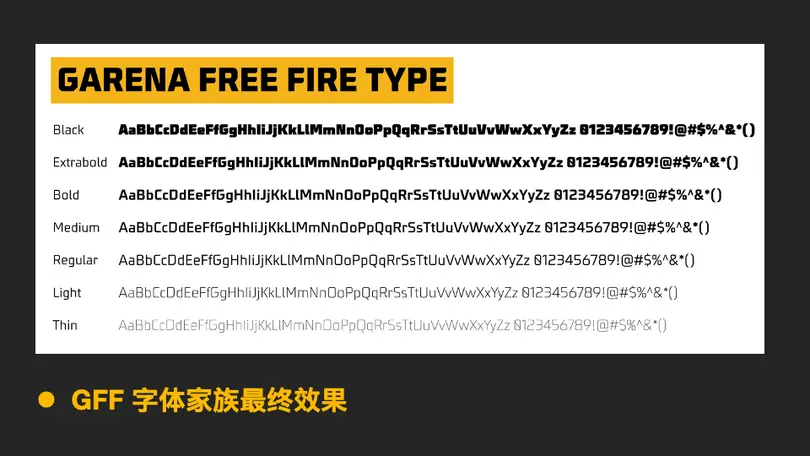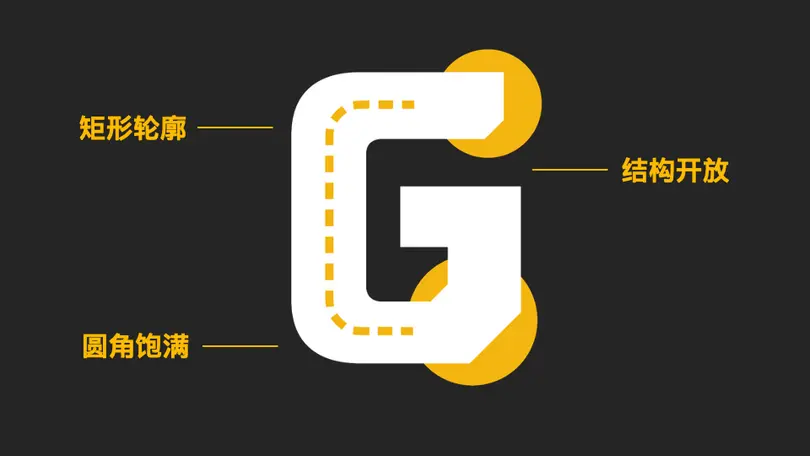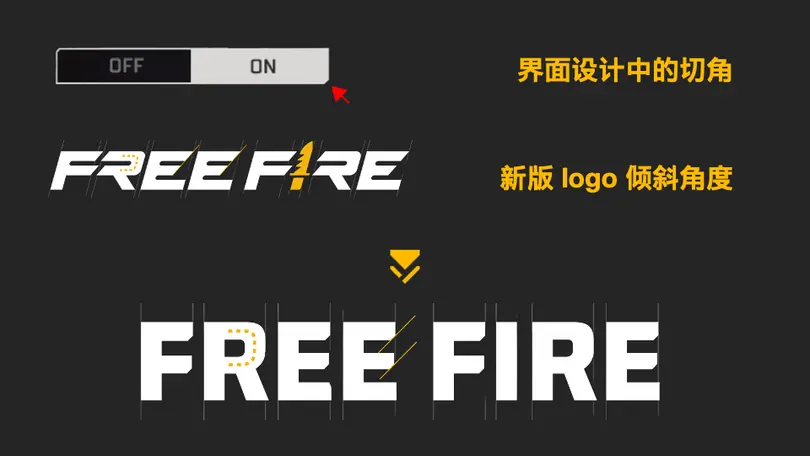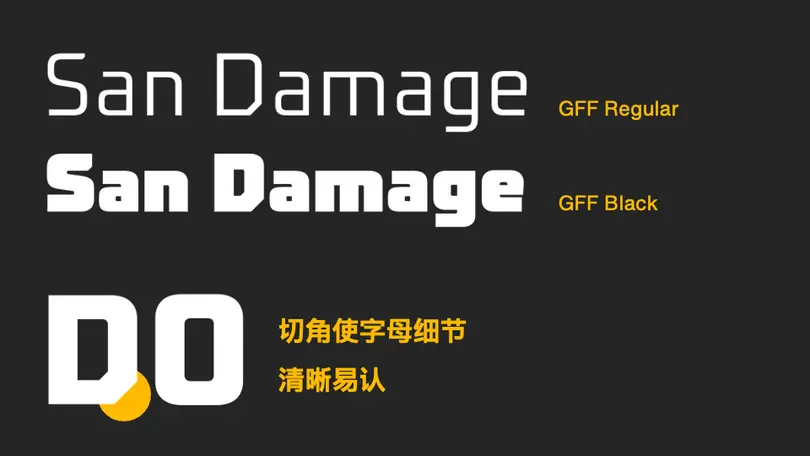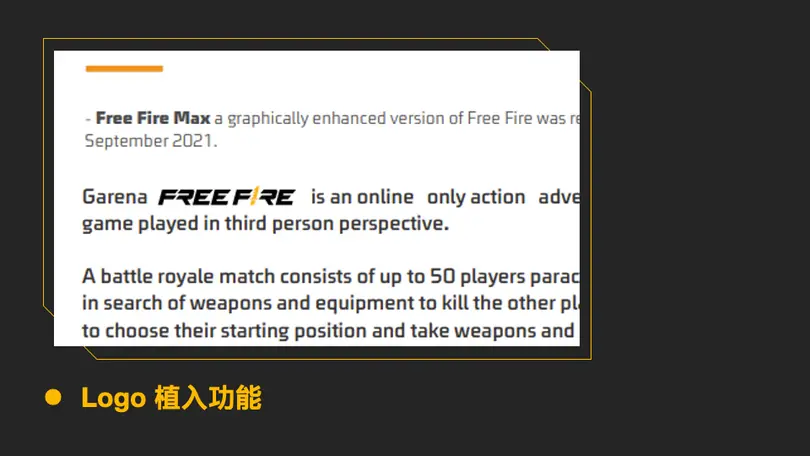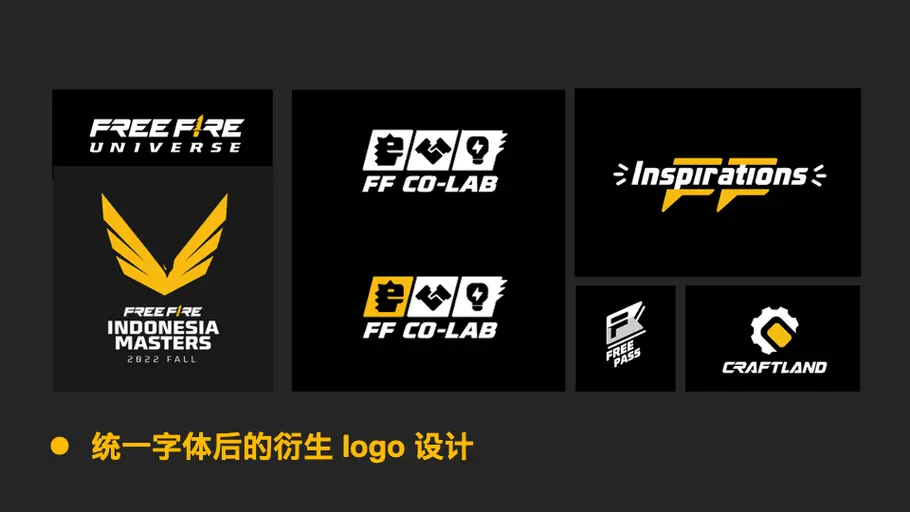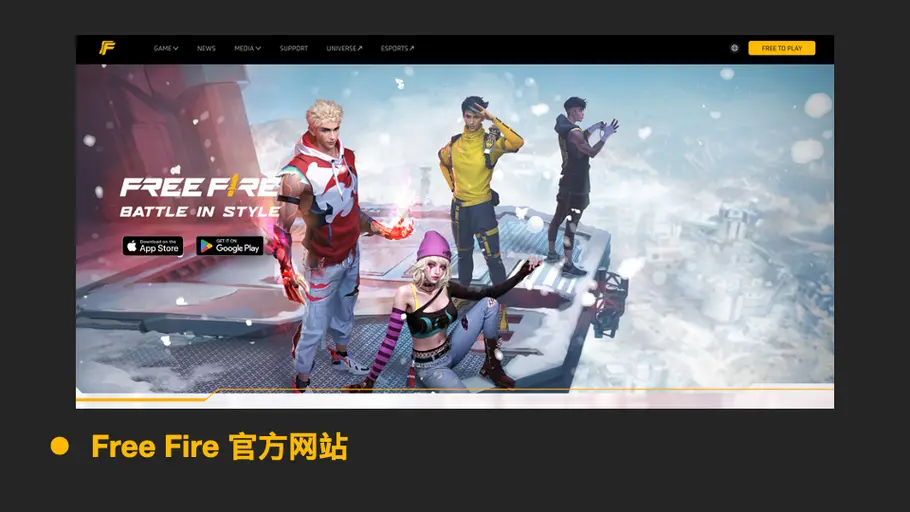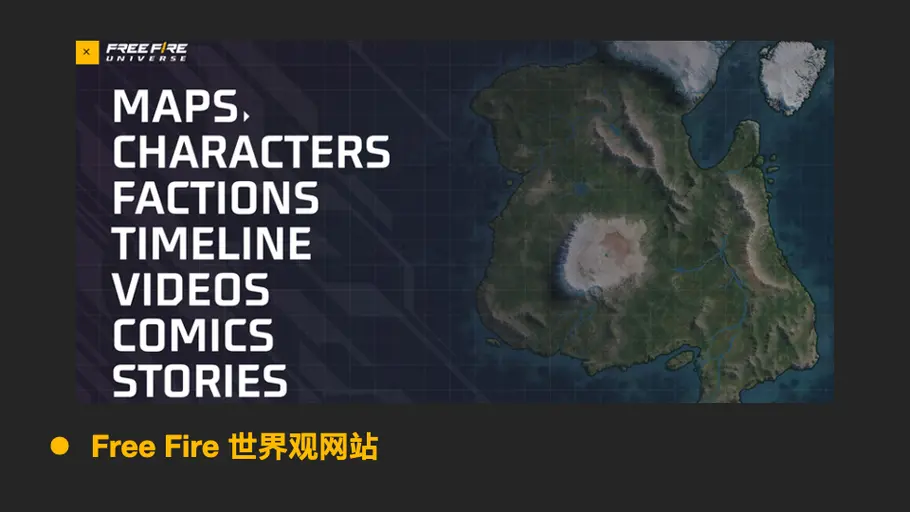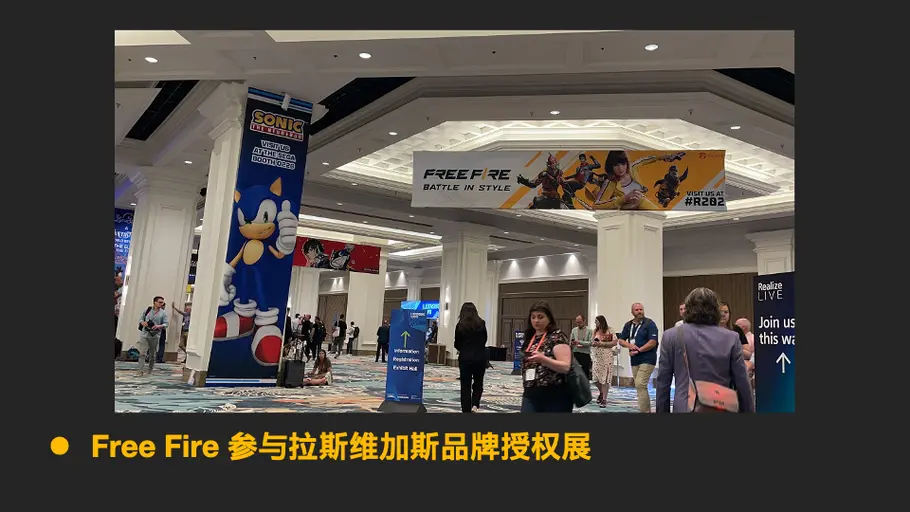
Garena 是知名的游戏开发及发行商,Free Fire 是其旗下自研的大逃杀类动作射击手游。自 2017 年发行至今,Free Fire 已向全球 160 多个国家和地区的玩家传递愉悦优质的游戏体验,在 2021 年达成了全球 10 亿次下载,曾连续三年问鼎全球下载量最高手游。
品牌升级挑战
伴随如此亮眼的成绩,Free Fire 在 2022 年迎来其发行五周年的里程碑,启动了游戏界面及品牌形象全方位的升级,并把“酷”与“轻”作为此次升级的视觉内核。
而字体的选用,逐渐浮现为升级过程中的关键环节。对于游戏界面,Free Fire 此前选用的授权字体虽然在风格上相对匹配,但字形窄粗,可读性欠佳,语种支持也有限;此外,自由度极高的本地化运营,也带来视觉形象不统一的潜在问题,其中字体的不统一成为主要原因。
字体设计细节
蒙纳字体创意总监小林章领衔指导的设计师团队与 Free Fire 团队紧密合作,对比多款现有字体,结合游戏应用实际需求,敲定了基础字形方案,并不断丰富更多细节,最终呈现 GARENA FREE FIRE TYPE 字体家族,简称 GFF Type。
风格与易读的极致平衡
GFF 基于矩形轮廓,结构开放,圆角饱满,笔画粗细均匀,构成了潮酷有力的基础风格。
同时,蒙纳设计师注意到了 Free Fire 界面设计中代表性的切角,以及新版 Logo 的倾斜角度,因此在笔画末端加入了统一的 45 度切角,使字体整体更科幻灵巧,尤其在粗体时极具表现力,“四两拨千斤”般彰显出品牌基因。
GFF 也在易认性方面表现出色。较高的 x 字高与开放的结构给予更多内白,精细调整后的字间距紧凑而不失均匀,从而保证阅读舒适感。切角的存在也使字母细节清晰易认,例如大写字母 D 与 O 得以区分,规避识别问题。
更多语种,更佳适配
GFF 除常规语言外,也支持许多拉美、中东及东南亚小语种,如葡萄牙语、阿拉伯语、泰语、越南语、印尼语等,从而为 Free Fire 运营全球市场提供了更为强大的语种资源。
对于多语言开发常见的文本预留问题,Free Fire 需要做到 100% 甚至更多,因此 GFF 除初版的 7 款字重外,还增加了 2 款窄体(Condensed),更好地适配开发。
除此以外,GFF 也应 Free Fire 的游戏交互属性,配备了更多亮点功能,如 Logo 植入功能、特殊字符定制等。
响应设计趋势
作为一款无衬线字体,GFF 在简洁的结构之上弱化手写感,并减少过度的棱角和冗余的线条,从而更为轻盈现代,干练耐看。
蒙纳字体创意总监小林章如此评价 GFF:“它与 Free Fire 的品牌风格一致,细节同步。小写字母简洁理性的外观使文本以轻快、冷静的方式发声。”
传递愉悦体验
GFF 一经推出,便得到了 Free Fire 团队及玩家的广泛认可。随着视觉升级完善,大量的衍生 Logo 设计运用到了 GFF,官方网站、世界观网站等完成了字体更新,线下展示与物料也能见到更多 GFF 的身影。
经由 Free Fire 与蒙纳团队的共同合作,GFF 为游戏本身确保了愉悦体验,也为多种媒介、多个触点赋予了更协调一致的设计语言。
Garena 艺术指导李振栋对此次视觉升级与字体开发总结道:“由于有了 GFF 的统一字形,我们的游戏及品牌一致度也得到了极大提高。我们希望给玩家创造更好的游戏体验,并将 BATTLE IN STYLE 的精神内核带入玩家的生活中去。”